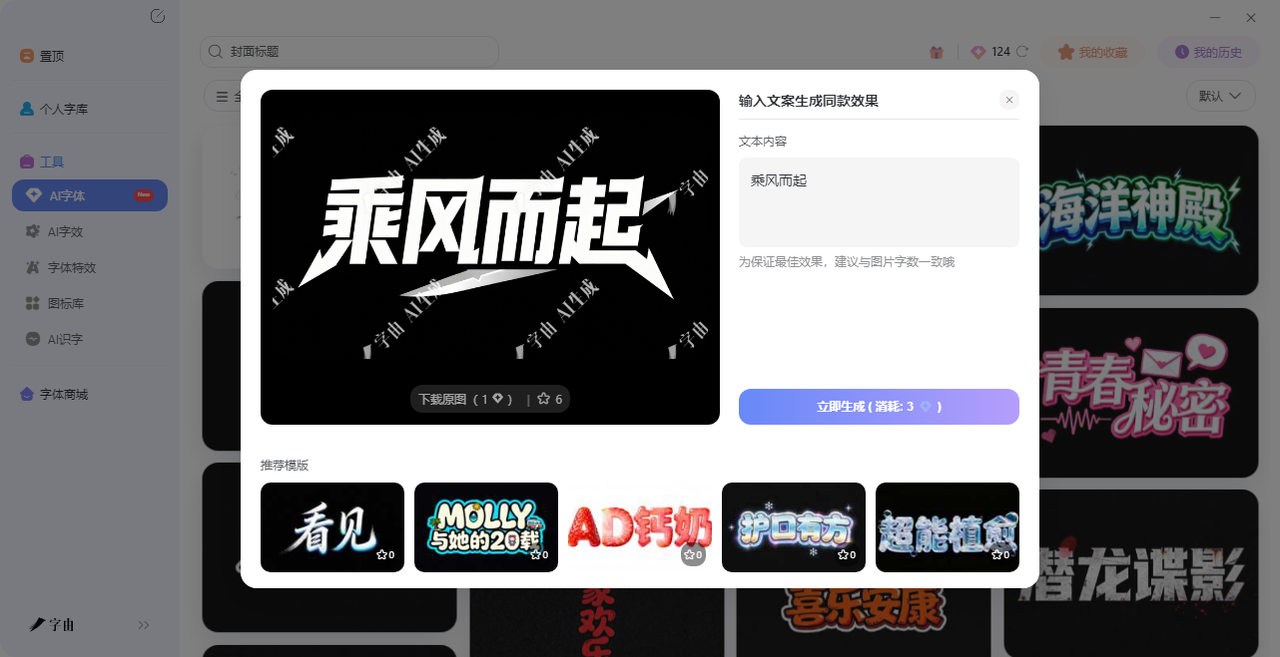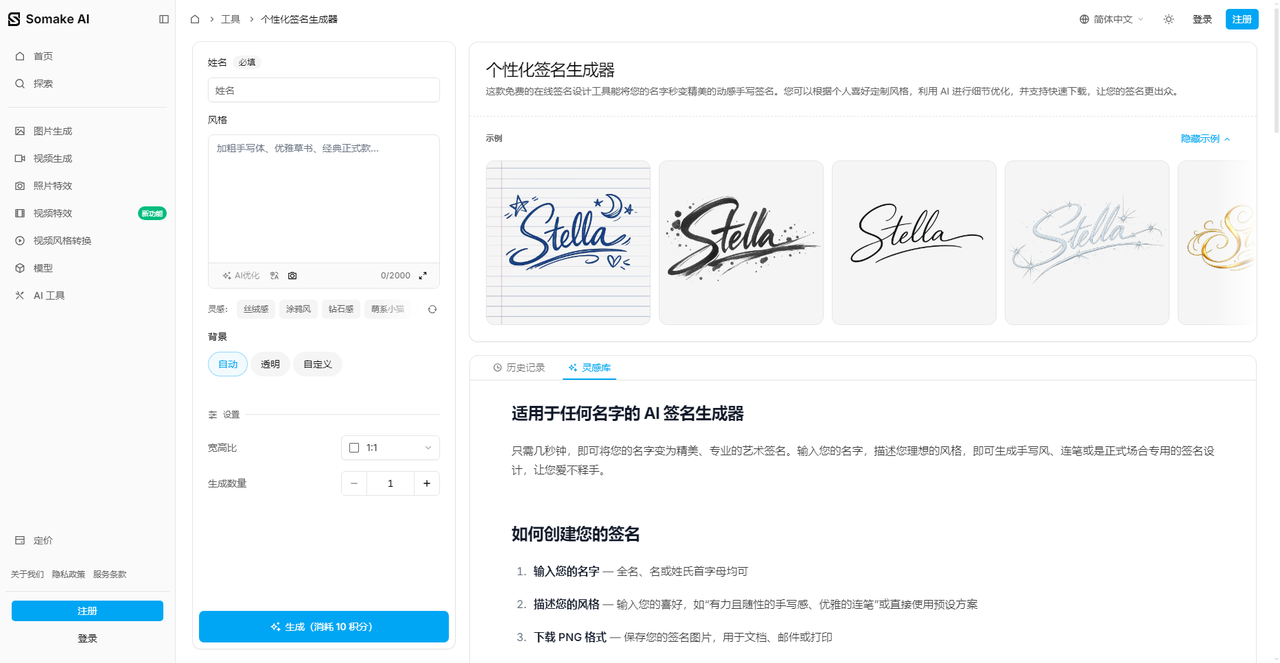
个性签名怎么设计?这几个网站一键帮你搞定
你有没有遇到过这种尴尬:签电子合同时,用鼠标歪歪扭扭写了几个字,自己都觉得丑;或者想给简历落款加个签名,但实在拿不出手。手写签名不是一天能练好的,但电子签名可以靠工具搞定。现在网上有不少签名设计网站,输入名字就能生成各种风格的签名。今天整理了6个签名设计工具,从字由的AI字体生成到专业签名网站,覆盖了AI生成、书法定制、一键出图等不同需求。看完这篇,你也能拥有一个拿得出手的签名。
字由收录了上万款字体,其中包含大量适合签名的书法体、手写体、艺术体。打开字由客户端,在筛选栏里勾选“手写体”或“书法体”,你会看到几十款风格各异的手写字体——有的像钢笔随手写,有的像毛笔蘸墨,有的带着涂鸦的随意感。找到喜欢的字体后,点一下“激活”,它就会自动出现在PS、Word的字体列表里。然后你打出自己的名字,就能直接用了。这种方式适合那些清楚自己想要什么风格的人。
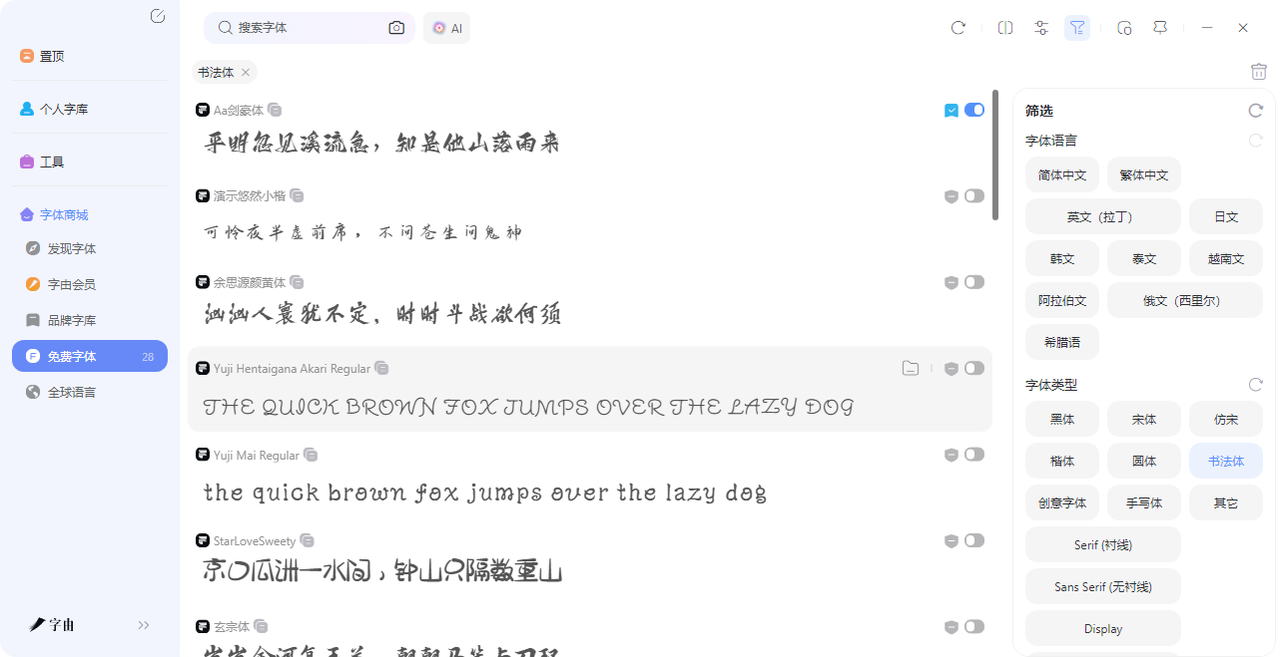
- 第二:AI字体一键生成签名图
如果你连翻字体库都嫌麻烦,字由的AI字体功能可以帮你直接“造”出一张签名图。打开字由客户端,找到“工具”里的“AI字体”,里面有400多种特效模板。选一个书法风或手写风的模板,输入你的名字,点“立即生成”,30秒左右就能得到一张设计好的签名图片。生成后可以下载透明背景的PNG,直接贴在合同、简历、邮件签名里。每天登录送免费
字由的三种方式正好对应了三种需求:字体库适合自己做选择,AI字体适合不想折腾的新手,云字库适合长期使用。
2、Somake AI
第二个工具是Somake AI。这是一个AI驱动的签名生成器,界面很现代。输入姓名后,你可以选择风格(加粗手写体、优雅草书、经典正式款等),还可以描述你想要的风格,比如“有力且随性的手写感”“优雅的连笔”。AI会根据你的描述生成对应的签名设计。生成后可以下载PNG格式,背景可以设置透明或自定义颜色。它还支持宽高比调节,适合不同场景使用。每次生成消耗10积分,注册登录后应该会有免费额度。如果你想要一个真正“个性化”的签名,而不是千篇一律的模板,Somake AI的AI定制功能值得一试。
3、曦之签名网
第三个网站是曦之签名网。这是一个主打“书法家定制签名”的网站,和前面那些AI生成的不一样。你可以输入姓名,选择样式(潇洒签、明星签、生肖签等),然后由书法家真人设计。网站还提供了百家姓签名视频展示,可以看到各种姓氏的签名效果。这个网站更适合那些对签名要求比较高、愿意花一点钱获得专属设计的人。如果你想要一个真正有书法功底的签名,而不是电脑生成的字体,曦之签名网是一个不错的选择。网站还提供了多种套餐,从免费设计到付费定制都有。
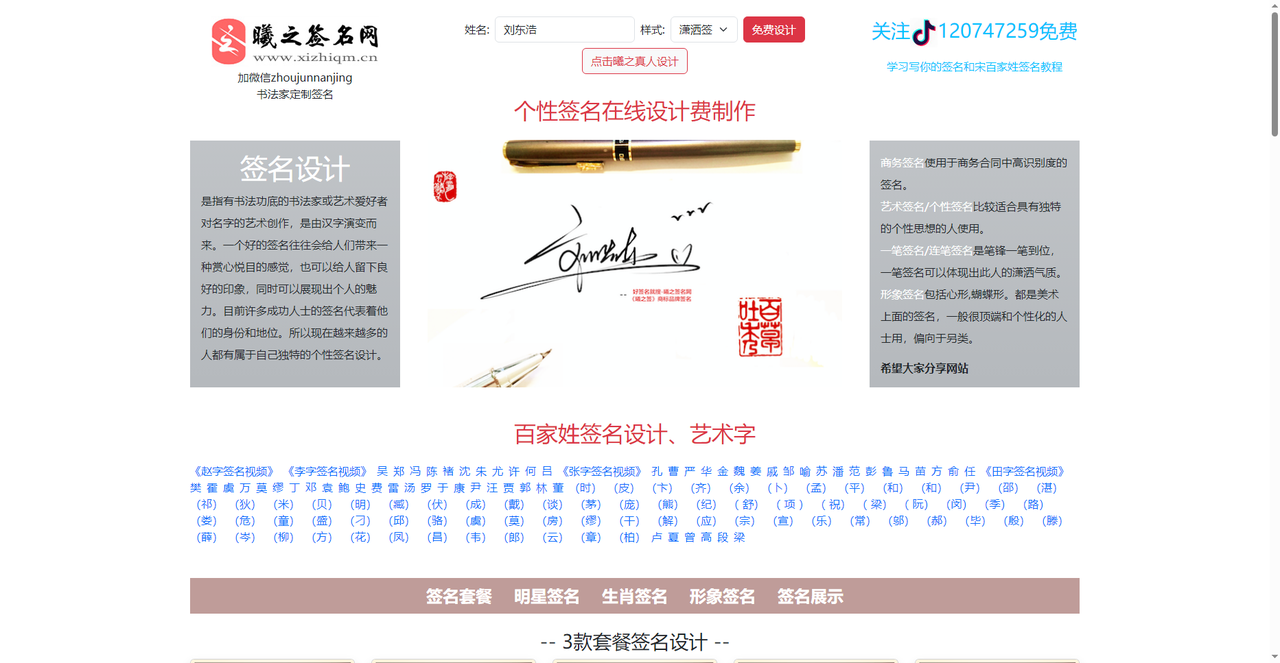
4、在线签名设计工具
第四个工具是一个简洁的在线签名生成器。界面很简单:输入签名文字,选择字体类型(花式签等),调节文字大小、字体颜色、背景颜色,然后点击“生成签名”。它没有复杂的AI功能,就是一个纯粹的参数调节工具。如果你想要一个快速、简单、不折腾的签名,这个工具最合适。不需要注册,不需要描述风格,选个颜色和大小就能出图。
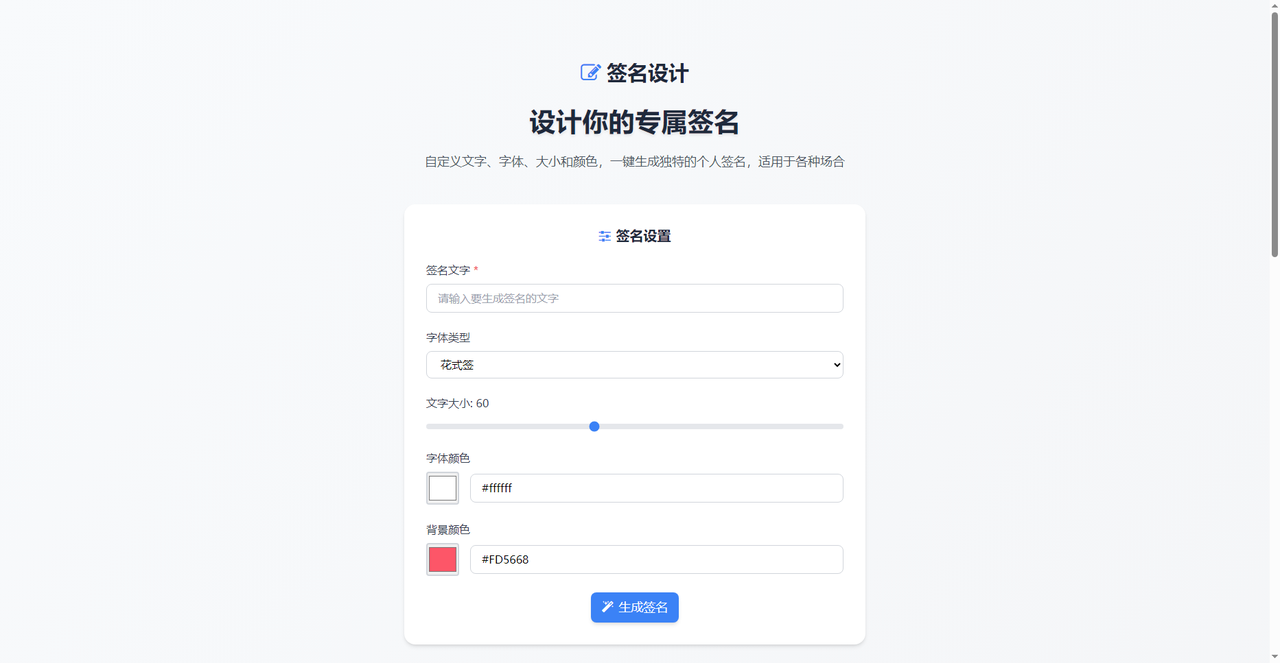
5、改图鸭
第五个工具是改图鸭。这是一个多功能图片处理平台,其中包含“艺术签名在线生成”功能。输入姓名(支持2-20字),选择字体(笔艺术签等),设置字体颜色、描边、背景颜色,还可以选择应用场景(比如“小樱桃女孩”这种风格预设)。点击“立即生成”就能看到效果。改图鸭的签名功能比较轻量,适合快速生成。如果你已经在用改图鸭的其他图片处理功能,顺手做个签名很方便。
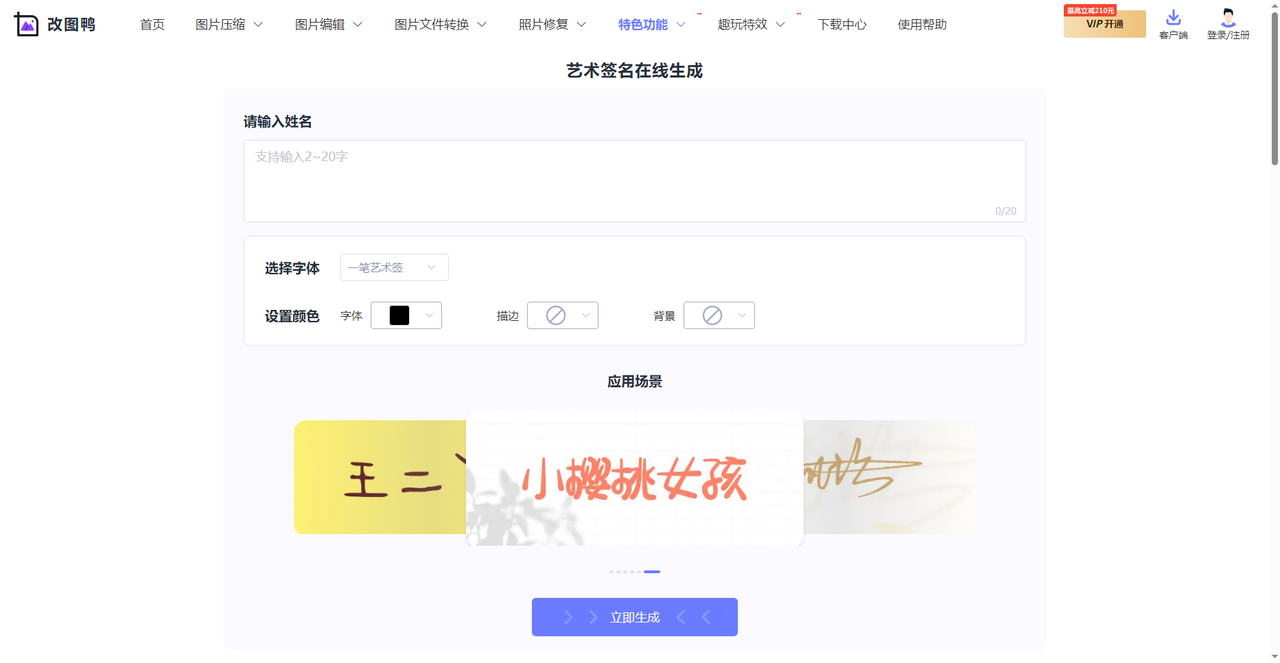
6、签名设计免费版在线
第六个工具是签名设计免费版在线。界面非常简洁:输入姓名,选择签名样式(艺术签等),点击“设计”按钮,就能生成专属艺术签名。网站还展示了一些示例签名(苏晓梅、陈明娟、鹿晗等),可以看到效果。这个工具主打免费、简单、无需注册。适合只想快速试一下效果、不想折腾任何设置的用户。
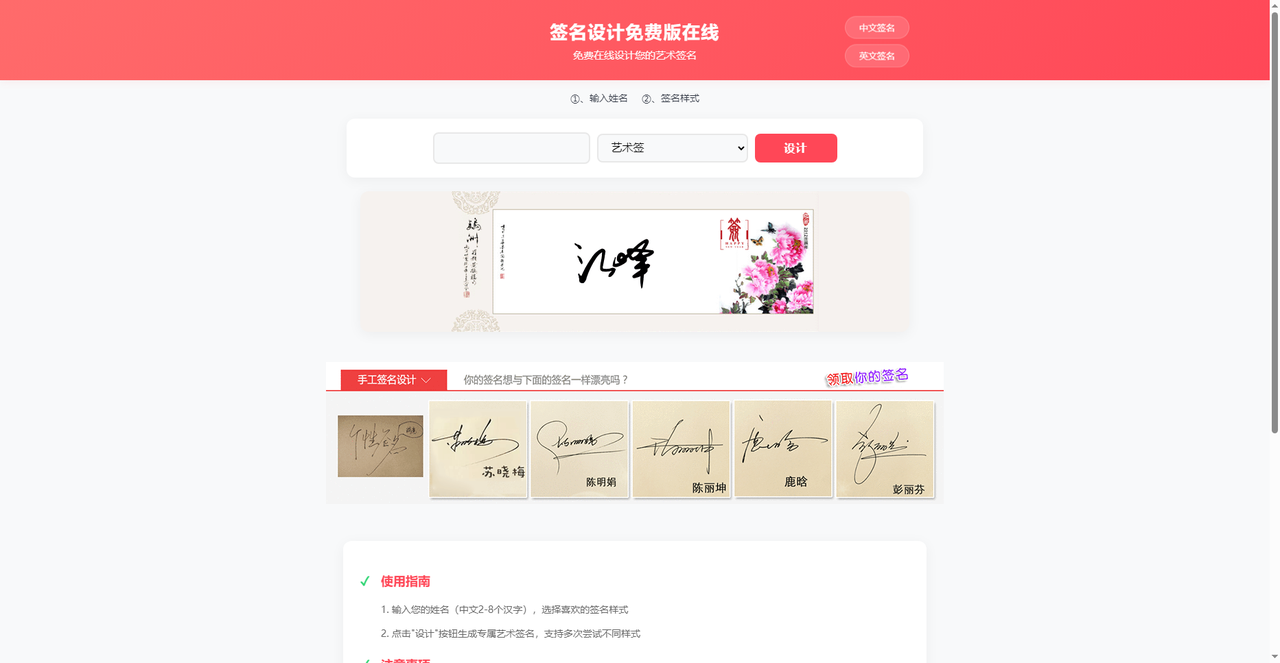
6个签名设计工具,各有各的用法。字由最适合设计师和需要长期使用多种签名风格的人,字体库+AI生成+云存储一键解决;Somake AI的AI个性化定制最智能,适合想要独特风格的用户;曦之签名网提供书法家真人定制,适合对签名有高要求的人;改图鸭和另外两款在线工具主打轻量快速,适合临时用一下。选哪个取决于你当下的需求——是要AI生成,还是真人定制;是要长期使用,还是临时凑合。这几个工具基本都是免费或低成本的,挨个试一遍,几分钟就能找到适合你的那个签名。